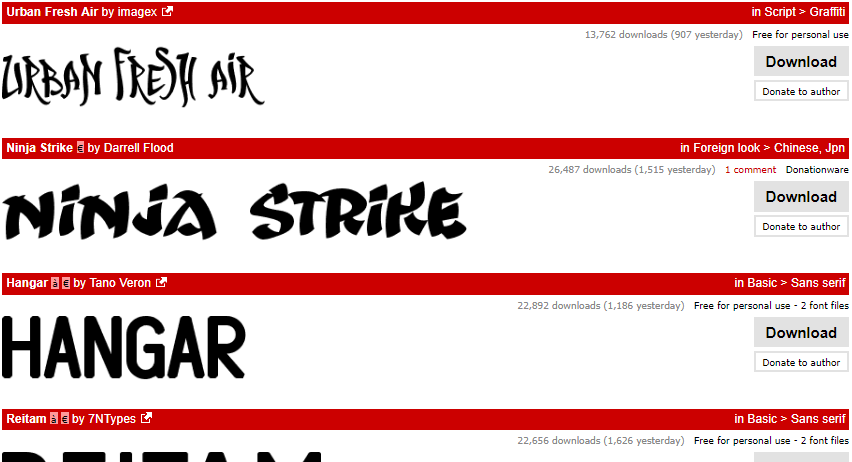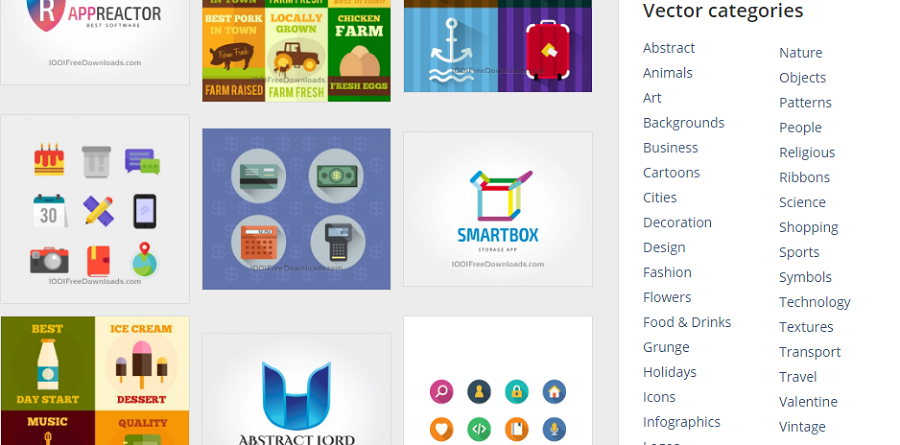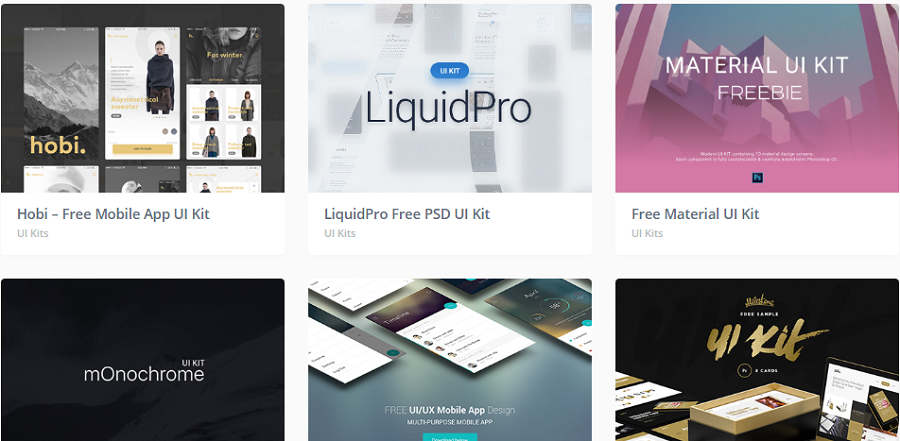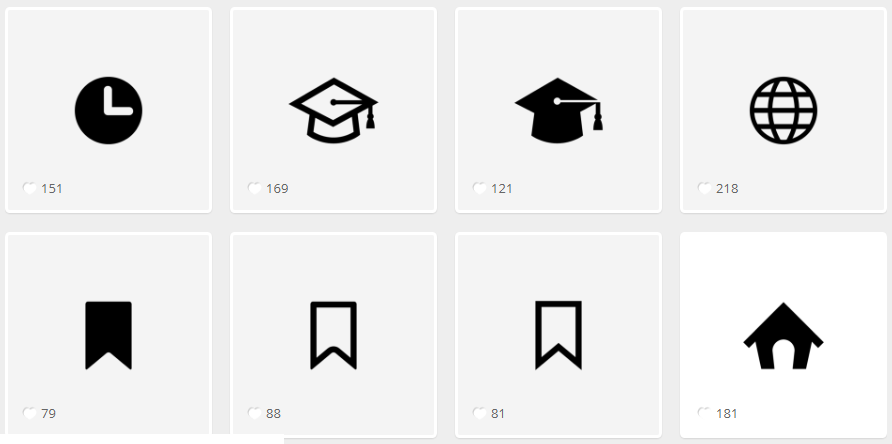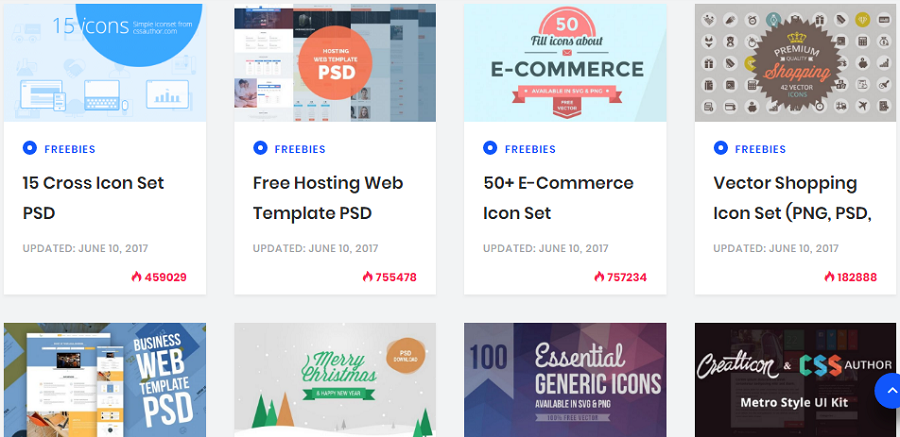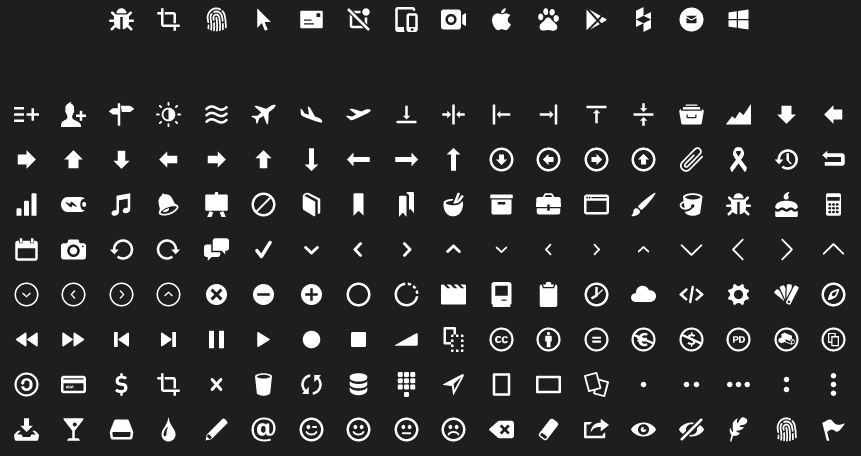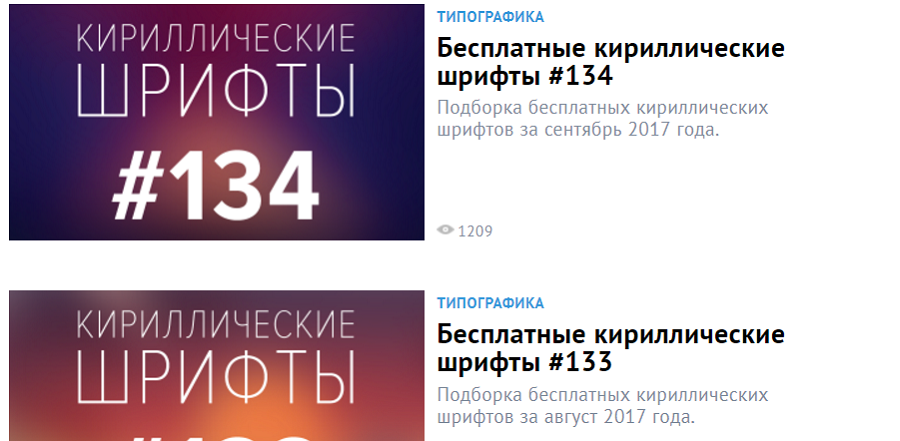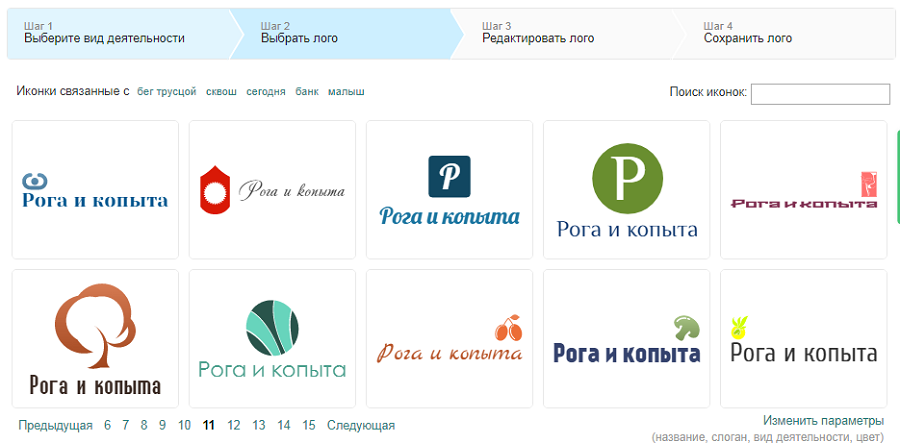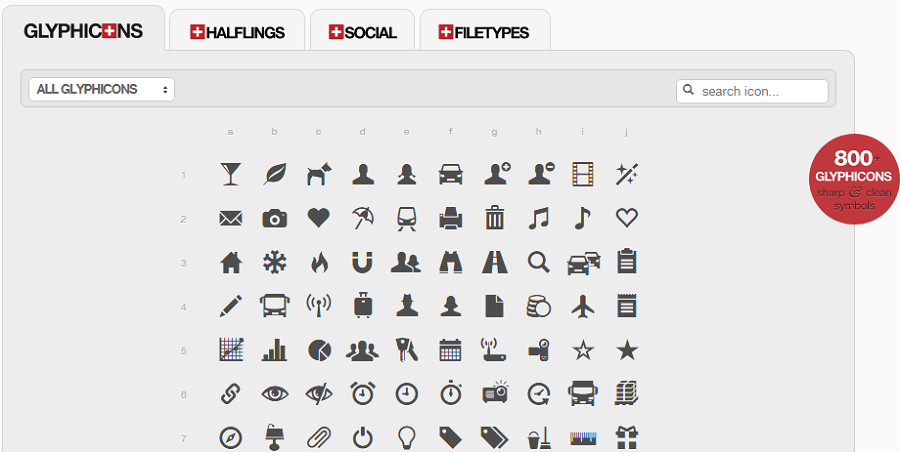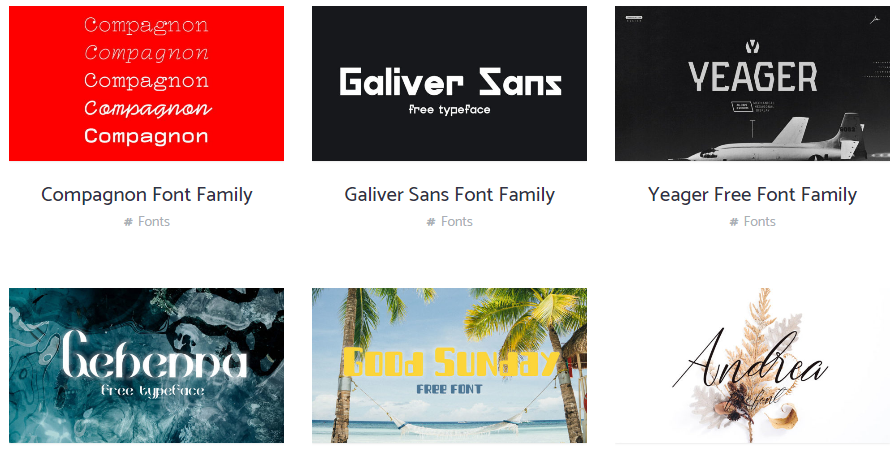
60+ ресурсов с бесплатными иконками, логотипами и шрифтами Редакция «Текстерры»
Чтобы сделать группу «ВКонтакте», сайт, презентацию или буклет чуточку дружелюбнее, необязательно нанимать команду дизайнеров и нарушать авторские права. Мы собрали сайты и архивы, в которых можно найти иконки, шрифты и шаблоны для бесплатного использования – сейчас все дизайнеры кусают локти.
Бесплатные иконки
Captain Icon
Марио из Испании предлагает бесплатно скачать 350 векторных иконок. Здесь нет определенной тематики, но много категорий: design, sports, social и др. Иконки доступны в EPS, PSD, PNG, SVG, SKETCH форматах. По отдельности скачивать нельзя, все наборы – в одном архиве.
Dryicons
Dryicons – сервис, созданный командой дизайнеров и программистов. Здесь больше 5 000 иконок в 77 наборах. Условия бесплатного использования – проставление обратной ссылки.
Ego Icons
Ego Icons созданы на основе базовых геометрических фигур: треугольников, шестиугольников, ломаных линий. Они представлены на сайте в форматах SVG, PDF, AI, SKETCH, EPS и ICONJAR. Бесплатно можно использовать только 100 иконок. Платный доступ ко всем 3 600 значкам стоит 127 долларов.
Endless Icons
Мин Ким основал Endless Icons, чтобы делиться креативом с дизайнерским сообществом. В библиотеке сотни бесплатных черно-белых иконок в PNG и SVG. Endless Icons можно использовать и в личных, и в коммерческих целях.
Entypo
Flaticon
Flaticon – огромное хранилище иконок от создателей Freepik.
Сайт предлагает свыше 500 000 векторных иконок, объединенных в 9 700 наборов. Они доступны для скачивания в форматах PNG, SVG, EPS, PSD и BASE 64. Прежде чем загрузить иконку, вы можете поменять цвет и выбрать размер.
Glyphicons
Ищете минималистичные и монохромные иконки – посмотрите на glyphicons.com, там их более 800. Благодаря веб-шрифту и формату SVG иконки можно использовать при разработке сайтов, инфографики, мобильных приложений под iOS и Android.
Good stuff no nonsense
Основатель проекта – Агата, дизайн-иллюстратор из Польши. Разработка иконок – ее хобби.
На goodstuffnononsence.com можно скачать 5 наборов бесплатных иконок. Кажется, что контента мало, но он – высочайшего качества. Автор оформляет иконки вручную, они выглядят прекрасно.
Icojam
Icojam.com принадлежит команде дизайнеров, создающих иконки более 10 лет. Часть наборов продают, часть – раздают бесплатно.
Умного поиска нет, иконки опубликованы в блоге.
Последнее сообщение оставлено почти год назад, но, возможно, вас заинтересуют ранние записи. На Icojam опубликованы тысячи ярких и красочных иконок.
Icon Archive
На iconarchive.com представлено более полумиллиона бесплатных иконок и почти 2 500 наборов. Так как библиотека большая, пользуйтесь фильтрами – ищите нужные иконки по стилю, категории и размеру, типу лицензии.
Сохранить иконку на компьютер можно в форматах PNG, ICO и ICNS.
Iconfinder
Пользователям iconfinder.com открыт доступ к 1 926 000 бесплатных и премиум-иконок.
Здесь большой выбор размеров, форматов и тем.
Iconmonstr
В библиотеке немецкого дизайнера Alexander Kahlkopf собрано более 3 800 черно-белых иконок. Они хорошо оптимизированы для веба и доступны в форматах SVG, EPS, PSD и PNG.
Иконки предназначены для коммерческого использования. Указывать автора не обязательно.
Icons8
На icons8.com – почти 57 000 иконок, база пополняется ежедневно. Интерфейс дружественный: удобно искать иконки, ходить по категориям, выбирать размеры и форматы.